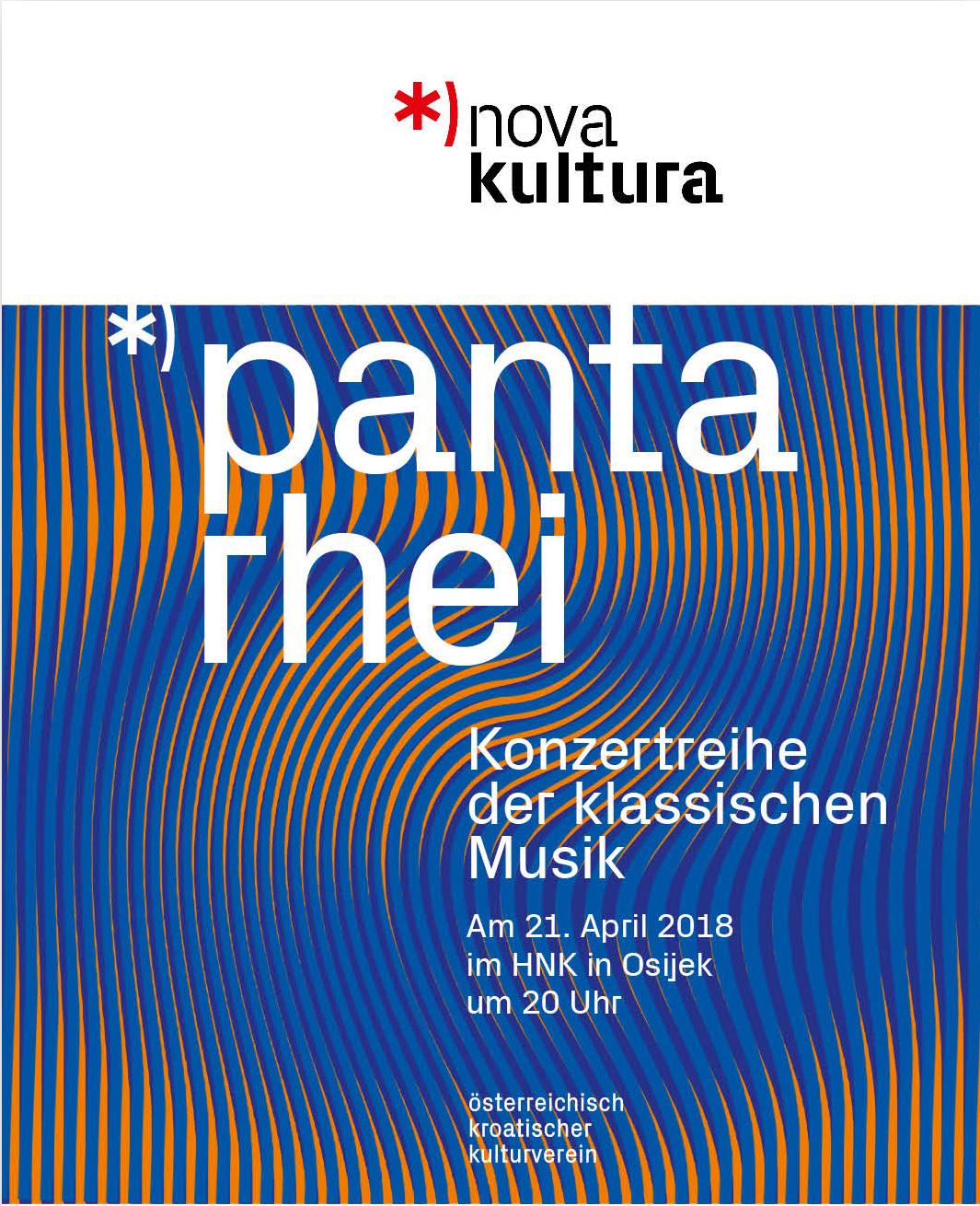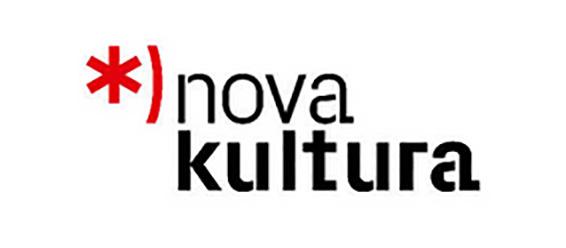
Gesucht: Stencil-Font für/von »Nova Kultura«
Ich bin auf der Suche nach diesem Stencil-Font, gebraucht wird die ganze Familie (falls es mehr als die gezeigten zwei Schnitte gibt).
Verwendet wird er in der CI, v.a. dem Logo des Österreichisch-kroatischen Kulturvereins „Nova Kultura“, Graz. Meine einzige Quelle: deren Facebook-Seite https://www.facebook.com/novakulturaat-1577532575662148/
Px Grotesk
Als Stencil hab ich ihn nicht gefunden, das wird vermutlich fürs Logo von Hand gemacht worden sein.
Das vermute ich, da sie nur im Logo vorkommen.